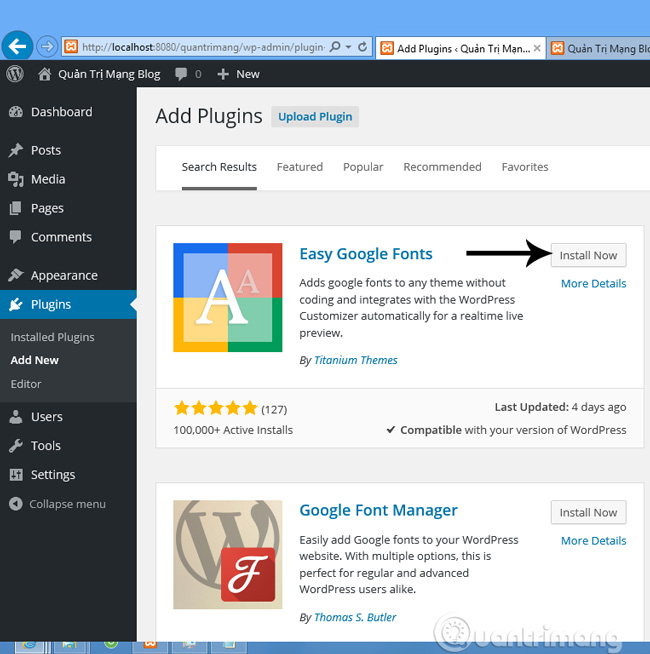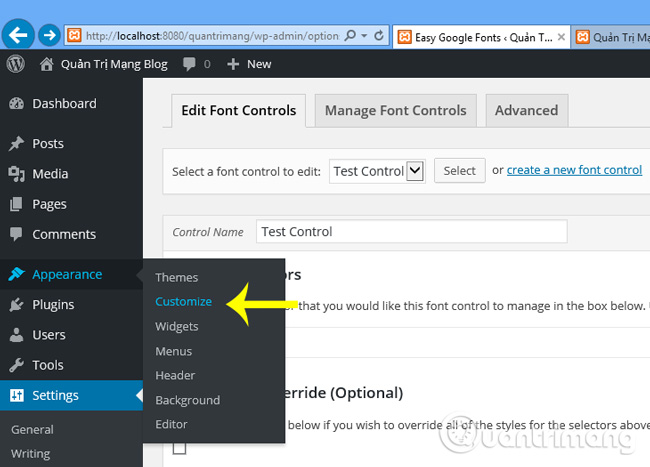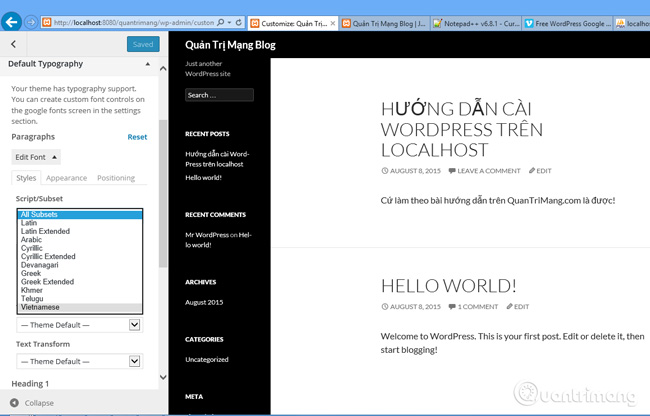
Làm thế nào để thay đổi font chữ trong WordPress
font mặc định của WordPress hiển thị tiếng Việt không chuẩn!
Khi đã cài đặt và thiết lập thành công WordPress trên localhost, các bạn mới nhận ra 1 điều: font chữ mặc định của WordPress khi gõ tiếng Việt nhìn không chuẩn, không được đẹp khi sử dụng cỡ chữ to, hoặc phóng to lên... Hay đơn giản là chúng ta muốn thay đổi font chữ mặc định của WordPress thì phải làm thế nào? Hãy cùng Quản Trị Mạng tham khảo qua bài viết dưới đây nhé!
font mặc định trên WordPress
Thực ra, cách làm chuẩn ở đây là chúng ta phải can thiệp vào CSS của WordPress, nhưng đâu phải ai cũng rành về CSS đâu? Do vậy chúng tôi xin giới thiệu với các bạn công cụ hỗ trợ rất hay và dễ sử dụng, đó là Easy Google Fonts.
Cách dùng Easy Google Fonts:
Đây được coi là 1 trong số những plugin tốt nhất trong việc tìm và áp dụng các font chữ đẹp của Google Font lên WordPress. Với Easy Google Fonts, người dùng có thể tùy chỉnh các loại ký tự, chỉ cần chọn chế độ Vietnamese là tất cả các loại font sẽ đều hỗ trợ chế độ gõ tiếng Việt, và đặc biệt là chạy tốt trên tất cả các theme. Mở phần Customize trong phần Apperance:
chỉnh sửa trong phần Customize
Cơ chế hoạt động của Easy Google Fonts là thay đổi chi tiết kiểu font cho tất cả các thành phần nội dung và tiêu đề (từ thẻ H1 đến H6), và do đối ở chế độ Customize nên chúng ta có thể xem trực tiếp kết quả mà không cần tải lại trang: